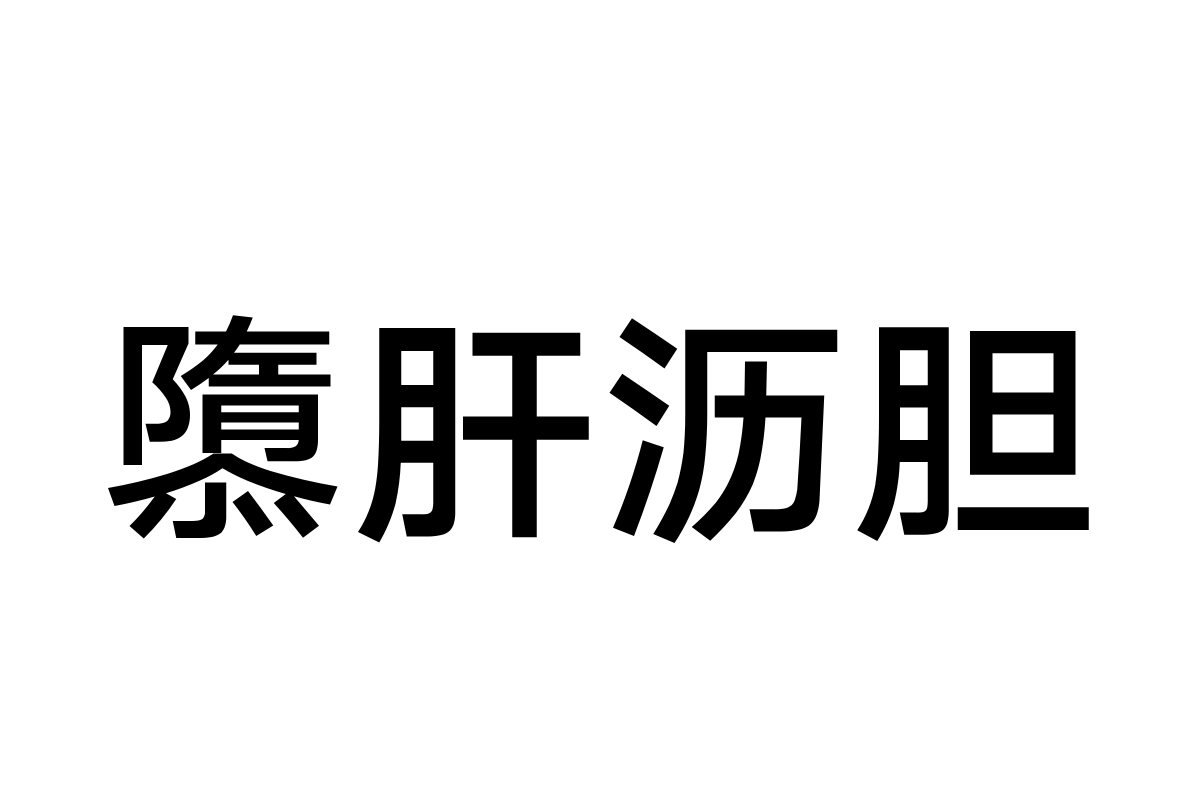
汉仪旗黑-65是一款具有独特风格的字体,它以其简洁、现代的设计风格而受到广泛欢迎。这款字体采用了简洁的线条和结构,使得文字看起来更加清晰易读。同时,它的笔画粗细适中,既不会过于夸张也不会过于细弱,给人一种平衡而舒适的视觉感受。
在设计上,汉仪旗黑-65注重细节的处理,使得每个字符都呈现出独特的美感。无论是字母的形状还是间距的大小,都经过精心设计,使得整个字体既有规律又不失个性。此外,这款字体还采用了一些特殊的设计元素,如装饰性的线条和图案,使得整体效果更加丰富多样。
总的来说,汉仪旗黑-65是一款非常实用的字体,无论是在网页设计、海报制作还是其他需要文字表达的场景中,都能展现出其独特的魅力。
汉仪旗黑-65